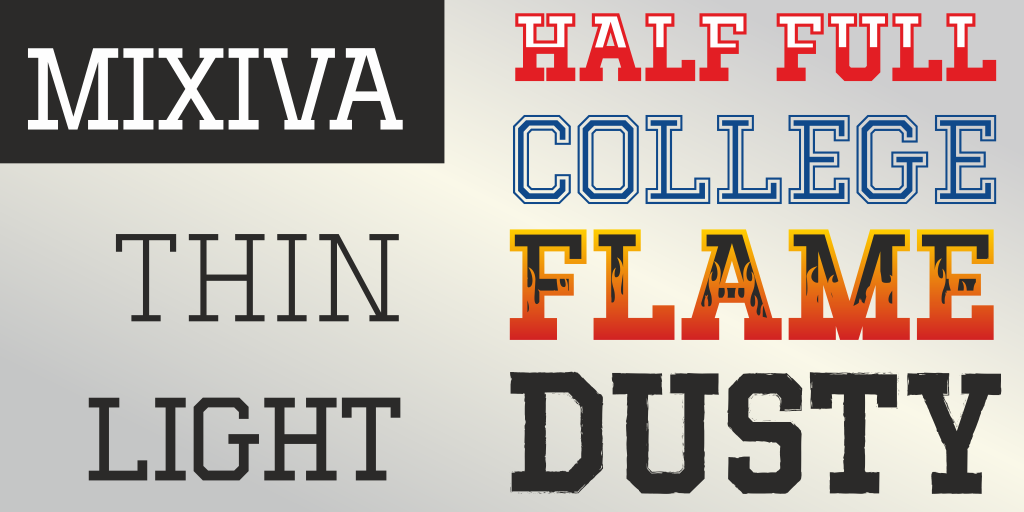
A fonte MIXIVA-DUSTY é uma slab serif que traz consigo uma atmosfera descontraída e envolvente. Inspirada nos desenhos livres e suaves do estilo Dusty, essa fonte de StudioTypo oferece um tom casual e aconchegante para qualquer projeto. Esta versão demo não inclui todas as letras do alfabeto, mas é uma excelente maneira de começar a experimentar os atributos únicos dessa fonte elegante e divertida. Para aqueles que desejam usá-la em projetos comerciais, o StudioTypo está disponível para assistência no site www.studiotypo.com. Há algo cativante nesta fonte para todos os gostos, seja você criando um layout de blog minimalista ou produzindo uma publicação amigável e descontraída. Não hesite em explorar mais sobre a MIXIVA-DUSTY; ela certamente encontrará um lugar especial no seu projeto.